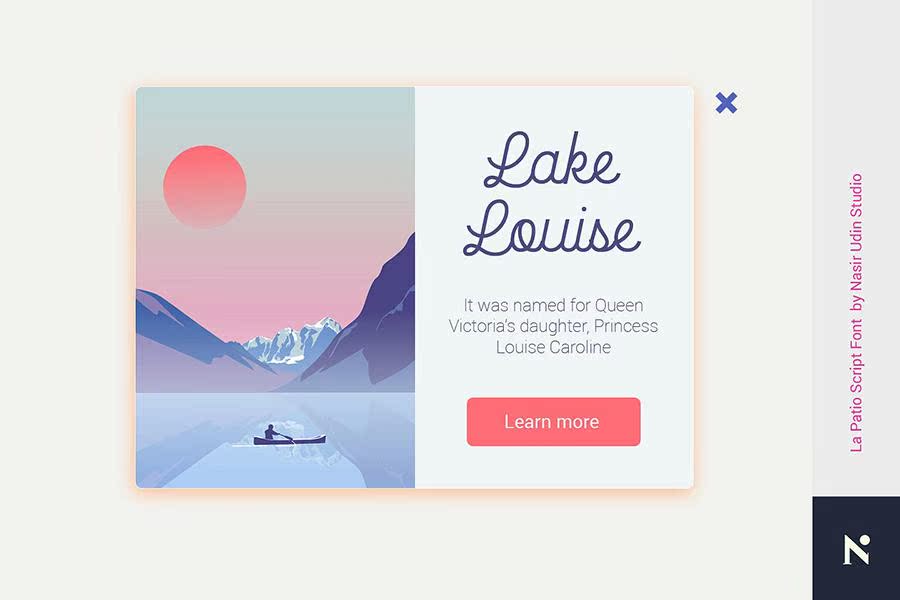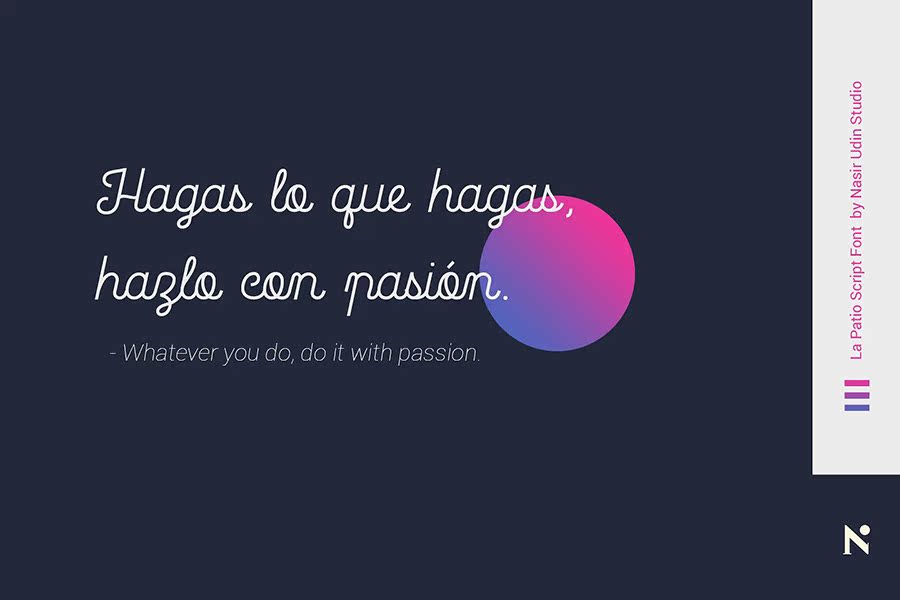
向La Patio脚本免费演示问好!单线脚本字体看起来像鞋带,很适合用作霓虹灯标志。拉帕蒂奥有几个备选方案和游泳池供你玩。此外,下划线和边框功能可帮助您为设计赋予特殊的个性。它是专门为服装品牌和标题排版设计的(例如:杂志、博客、书籍等)。它也是海报、名片、餐厅/酒吧/咖啡厅装饰、霓虹灯标牌、墙壁标牌、徽章等的完美之选。它是一种PUA编码字体,可以通过使用操作系统的实用程序(如字符映射(Windows)和字体手册(Mac)以及Illustrator、InDesign、Photoshop等)在任何程序中使用。